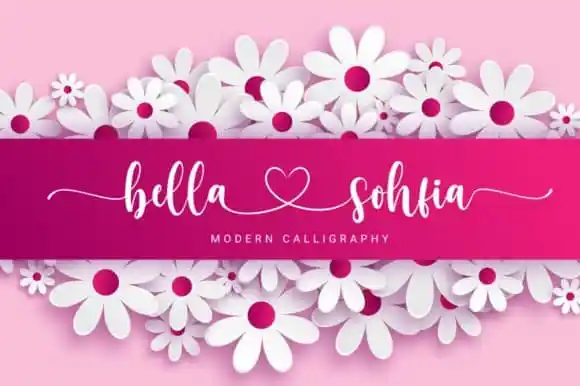
Bella Sohfia Calligraphy Font – Download Grátis
Descubra Bella Sohfia, uma elegante e romântica fonte escrita à mão que combina a simplicidade do tipo com os detalhes delicados de letra entrelaçada. Desenvolvida pelos arquitetos digitais da 99designs, essa fonte inclui todos os caracteres alfabéticos, números e pontuação necessários para fazer sua criação virar arte. A Bella Sohfia é uma opção perfeita tanto para Instagram posts quanto para projetos de DIY envolvendo escrita à mão. Ela oferece uma variedade no nível da linha de base, linhas suaves e formas exuberantes que garantem um visual único e agradável. Além disso, conta com alternativas incríveis, o que torna a criação de diferentes efeitos visuais ainda mais acessível. O PUA Encoding oferecido pela Bella Sohfia é uma vantagem significativa, permitindo que você facilmente accede a todos os caracteres e ligaduras. Esta característica garante um estilo fácil e fluente, o que torna Bella Sohfia uma fonte versátil para aqueles artistas digitais buscando um recurso de escrita à mão perfeita.